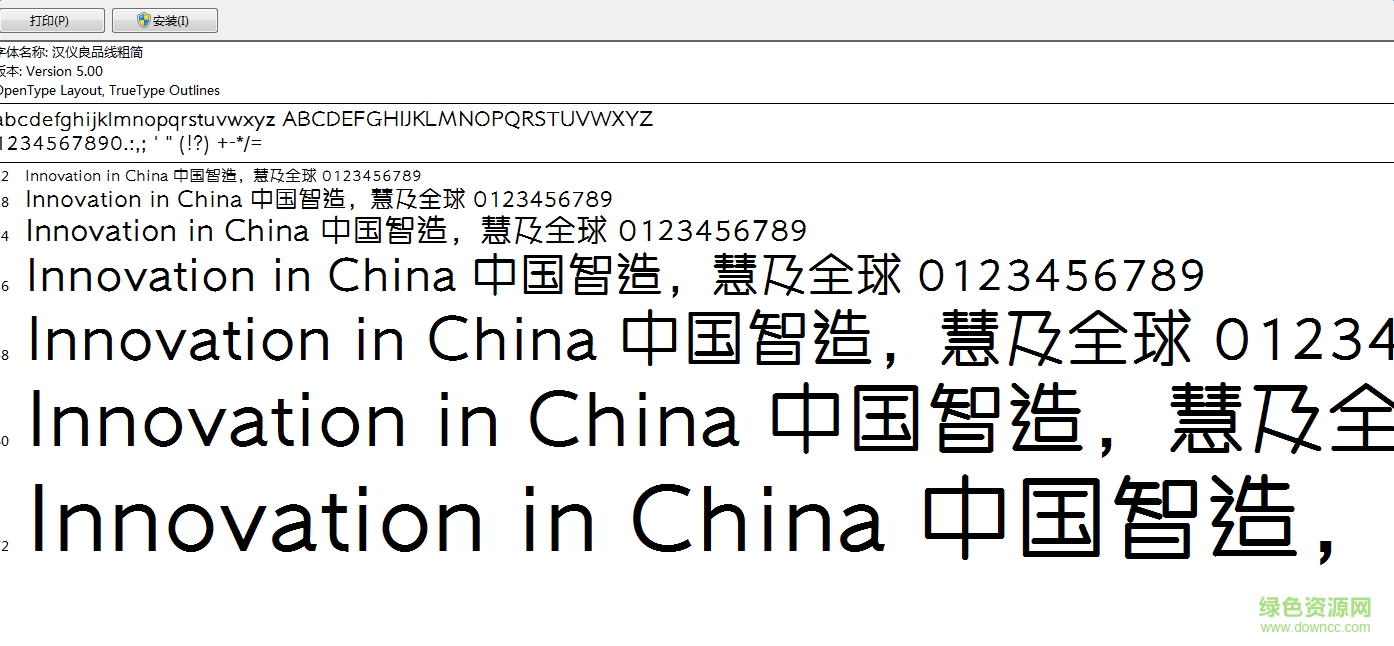
漢儀良品線粗簡(jiǎn)體
這款漢儀良品線粗簡(jiǎn)字體清新規(guī)整,充滿簡(jiǎn)約的設(shè)計(jì)感,整套字具有現(xiàn)代感。適合畫冊(cè)標(biāo)題、海報(bào)設(shè)計(jì)、廣告宣傳等場(chǎng)合使用!喜歡的朋友歡迎來(lái)綠色資源網(wǎng)下載哦!